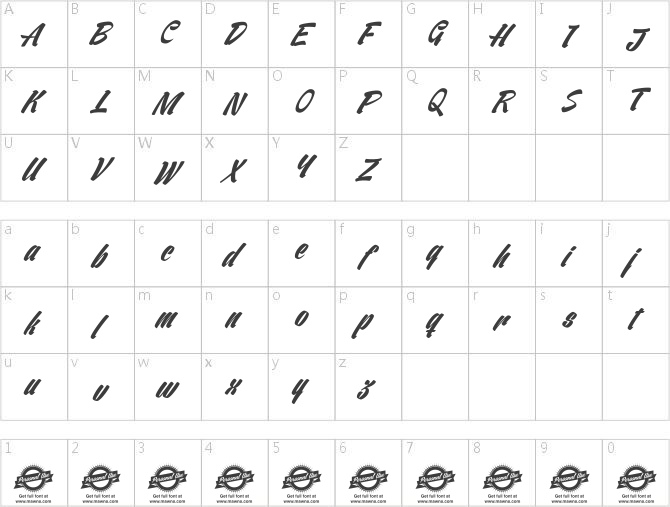
Ventography_Personal_Use_Only 詳情頁
字體名稱: Ventogr
Ventography_Personal_Use_Only
Ventography_Personal_Use_Only介紹
Ventography_Personal_Use_Only字體字庫是一款讓人賞心悅目、百看不厭的英文字體,適合各類廣告和產品包裝設計應用,字體大小0.18MB,格式為ttf字體,上傳用戶是一直在守護,作者/版權方為未知